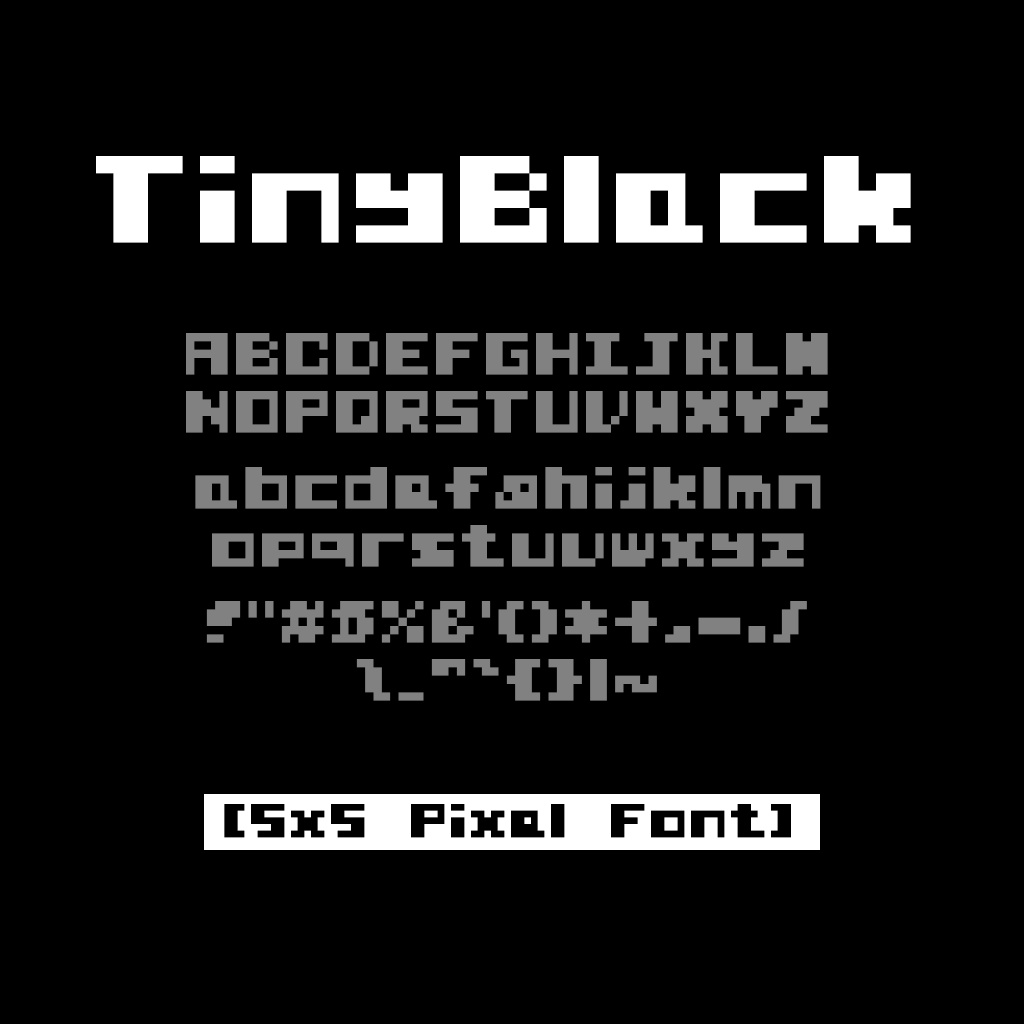
nuskeyTinyBlack - 5x5ピクセルフォントDigital0 JPY免费下载TinyBlack-Font.zip (70.1 KB)TinyBlack-Font.zipAbout Gift【TinyBlack】 TinyBlackは5x5サイズで構成された、小さく力強いピクセルフォントです。英数字と記号を含む94文字が収録されています。 作成時に用いた.asepriteファイルも同時に配布しているため、ase2ttfなどのツールを用いて簡単に改変が行えるようになっています。 SIL Open Font Licenseの下で公開されているため、商用利用を含む自由な利用が可能です。nuskeyVisit FANBOX!Fontsase2ttf Fontnuskey0 JPY